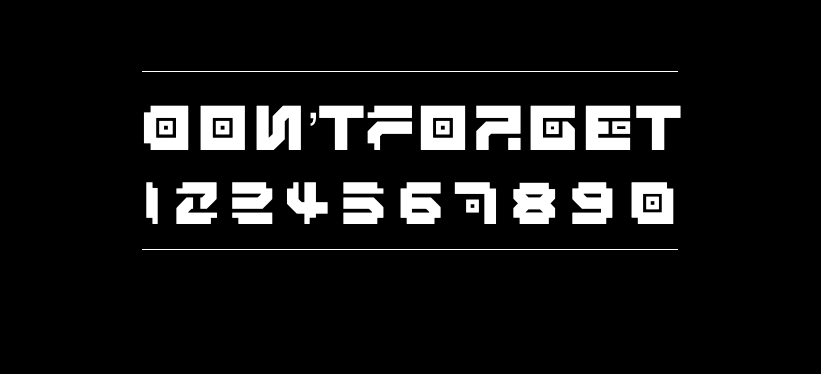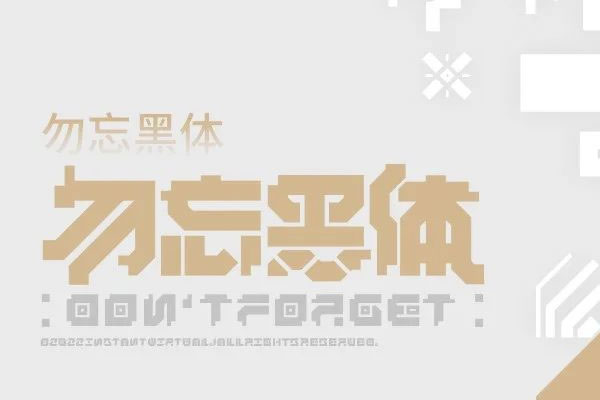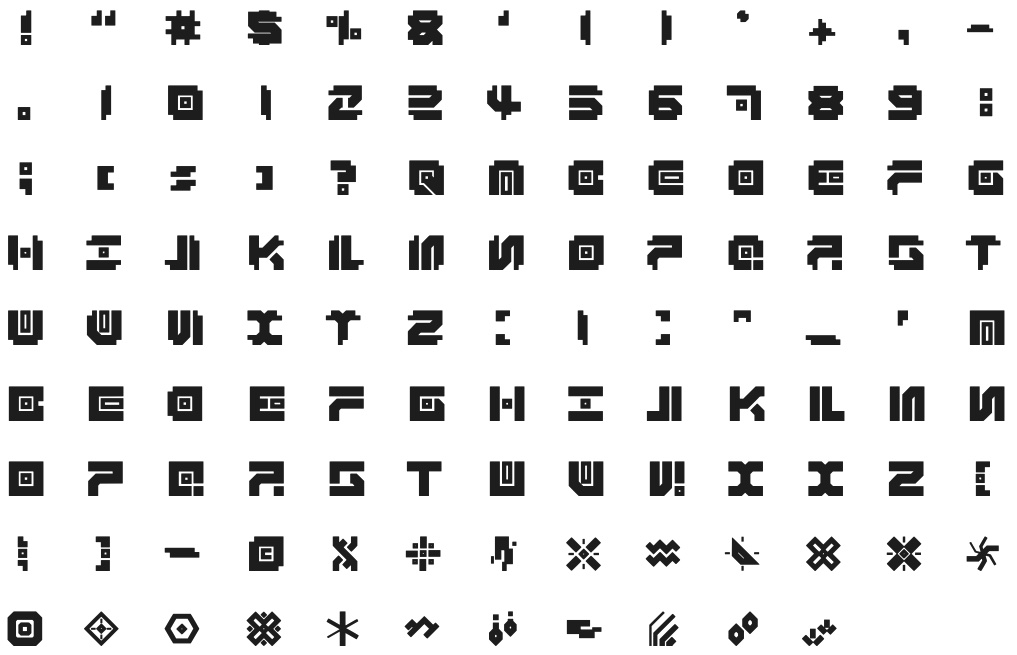
勿忘黑体
勿忘黑体(Don’t forgetWW)的作者是网友刹那仮想,勿忘黑体是一款装饰性字体,不推荐使用在正文排版设计当中。
推荐使用场景:风格化标题、点线面装饰。
以下是作者发布字体的原文引用:
勿忘黑体是我以普玛彭古和一些古文明为灵感创作的一款基于英语的装饰性字体,
你可以通过修改字体的间距,改变字与字的连接以达到传达不同感受的目的;
还可以将残缺部分拼接成新的图形,字体还包含连字图形和部分符号,
小写字体会减少部分细节。
自从人类文明出现以来,人们一直都在思考如何传达思想与记录,古文明中人们用石头创作艺术
和文学,推动了社会的发展。因为石头的特性能保存非常久的时间,后人也能了解学习前人的发
展历史。勿忘黑体是一款结合了古文明遗址、壁画、文字艺术的具有复古与未来感的实验字体。该
字体的字面非常大,我舍弃了部分辨识度让它看起来像是某种符号,正方形的字形传达出
一种神秘的无机感。勿忘黑非常适合用于创作具有未来、神秘感的视觉作品当中。我把大自然界中的部分元素以几何图形的形式表现出来,
我想传达一种从具象到抽象有机到无机的转换中形成的“距离感”。你可以通过调整字体间距连接字与字组成新的形状感受,
另外还可以将文字残缺部分拼接成新的图形,适合用于装饰画面。
之所以我把这款字体命名为“勿忘黑体”,是因为想通过这款字体传达出在当今快节奏的
信息时代当中,人们失去了自我判定能力,迷失了自我的发展方向。古文明中文字的发明
是人类社会发展非常重要的标志之一,也提高了人类的思维能力,我希望人们不要“忘记”
人类天生的求知欲望。“勿忘”象征了满足了物质需求的同时本能的去探索挖掘事物本质
以及达到更高精神追求。